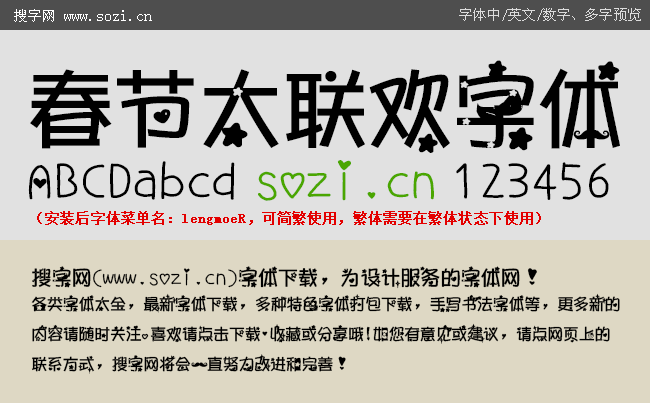
春節(jié)大聯(lián)歡字體
搜字網(wǎng)給大家提供一款很適合新年的手機(jī)中文字體下載。修改者給這款字體叫春節(jié)大聯(lián)歡字體,這款手機(jī)中文字體以POP字體為原形,在筆畫間嵌入卡通星星和愛心圖形,該中文字體趣味性強(qiáng),又保持了文字的識別度,非常適合喜慶熱鬧的新年期間在手機(jī)上安裝使用。